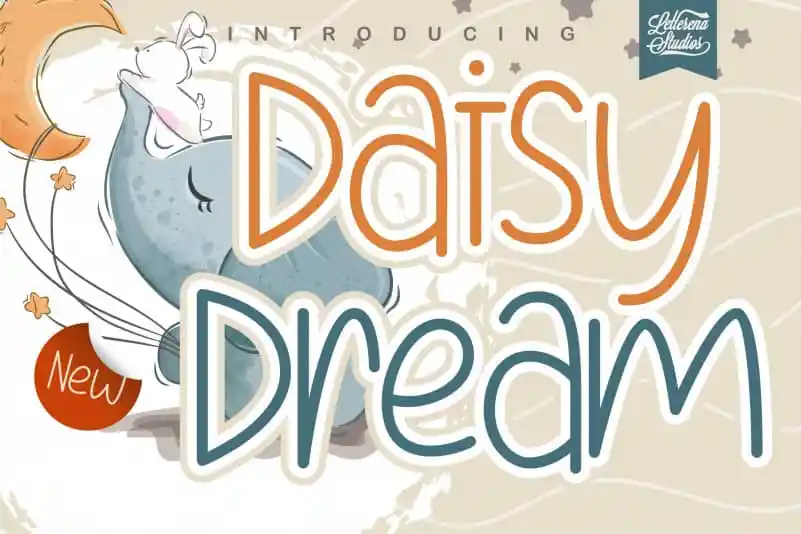
Daisy Dream Script Font – Download Grátis
A Daisy Dream Script Font é uma opção perfeita para quem busca um visual contemporâneo e despojado. Desenhada por letterenastudios, esta fonte em script apresenta um estilo simples e natural, que se adequa perfeitamente a qualquer projeto de design. Suas linhas leves e o tom delicadamente retrô oferecem uma combinação única que vai bem com designs modernos e trendy sem abrir mão da elegância de um estilo mais convencional. Perfeita para quem busca uma fonte divertida, autêntica e acolhedora no seu próximo projeto gráfico.